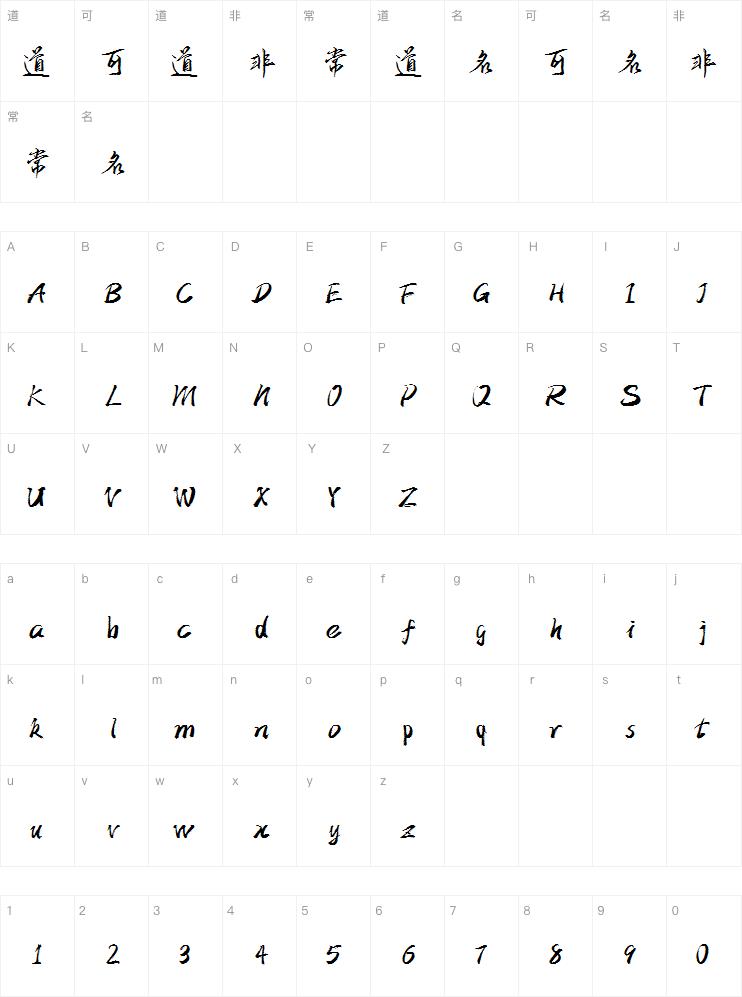
字小魂歌以晓手迹行楷体
字小魂歌以晓手迹行楷
字小魂歌以晓手迹行楷体字体是一款商用的硬笔手写,毛笔书法,英文手写,行楷,手写体,书法字,创意书写,硬笔字字体,该字体包含6763个中文、字母、 符号和数字,具有女性、优雅、浪漫、中国风的风格,可以满足您设计上的各种需求,该字体适用于店铺、活动、美食餐饮、健康养生等场景。